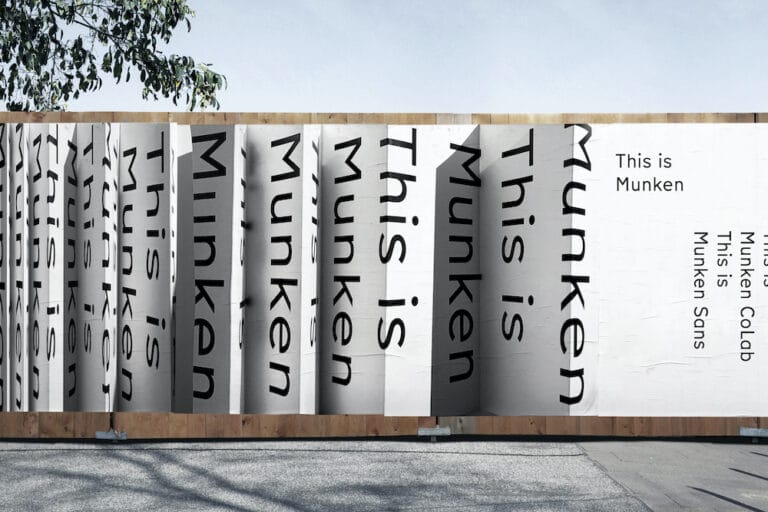
Der schwedische Papierhersteller Munken verschenkt seinen Corporate Font Munken Sans.
Die Branding- und Designagentur JUNO aus Hamburg entwickelte für Munken ein neues Erscheinungsbild, das die naturverbundene und schwedische Persönlichkeit der Marke in den Vordergrund stellt. Die neue Schrift Munken Sans kommt dagegen aus der Schweiz. Sie wurde von den Schriftdesignern Laurenz Brunner und Selina Bernet im Austausch mit Jonas Williamson und Cornel Windlin von der Foundry Lineto gestaltet.
Inspiriert ist die Groteskschrift von der klassischen schwedischen Schriftart Tratex von Kåge Gustafson aus den 60er Jahren, die man heute noch auf vielen Verkehrsschildern in Schweden sieht.
»Seit ich denken kann, faszinieren mich Straßenschilder. Schon während meiner Studienzeit, als ich lernte, Schriften zu entwickeln, war die Verkehrsschrift der Schweizerischen Normen-Vereinigung eine Inspiration für mich. Es beeindruckt mich immer noch, wie diese Buchstaben es schaffen, einerseits bei hoher Geschwindigkeit lesbar zu sein und gleichzeitig Details aus ihrem Herstellungsprozess zu offenbaren,« sagt Laurenz Brunner. »Eine heutige Version der Tratex zu denken und zu entwickeln war eine aufregende Herausforderung – es galt dabei das Original zu feiern, es aber auch gleichzeitig für den Einsatz auf und neben der Straße zu modernisieren.«
Das Ergebnis heißt Munken Sans und liegt in den drei Schnitten Regular, Medium und Bold vor. Ein 448 Seiten starkes Handbook präsentiert die neue Schrift Munken Sans auf spielerische Weise. Gedruckt auf Papier aus der Munken Design Range, zeigt das Buch verschiedenste Anwendungsmöglichkeiten der Schrift rings um die Themenfelder Natur, Schilder und Papier. Das Handbook, ebenfalls von JUNO gestaltet, ist gleichzeitig eine Hommage an das Buch als haptisches Objekt aus Papier.
Die Schrift Tratex aus den 60er Jahren diente Laurenz Brunner als Inspiration für die Munken Sans.
Das Handbuch präsentiert die Schrift auf spielerische Weise.